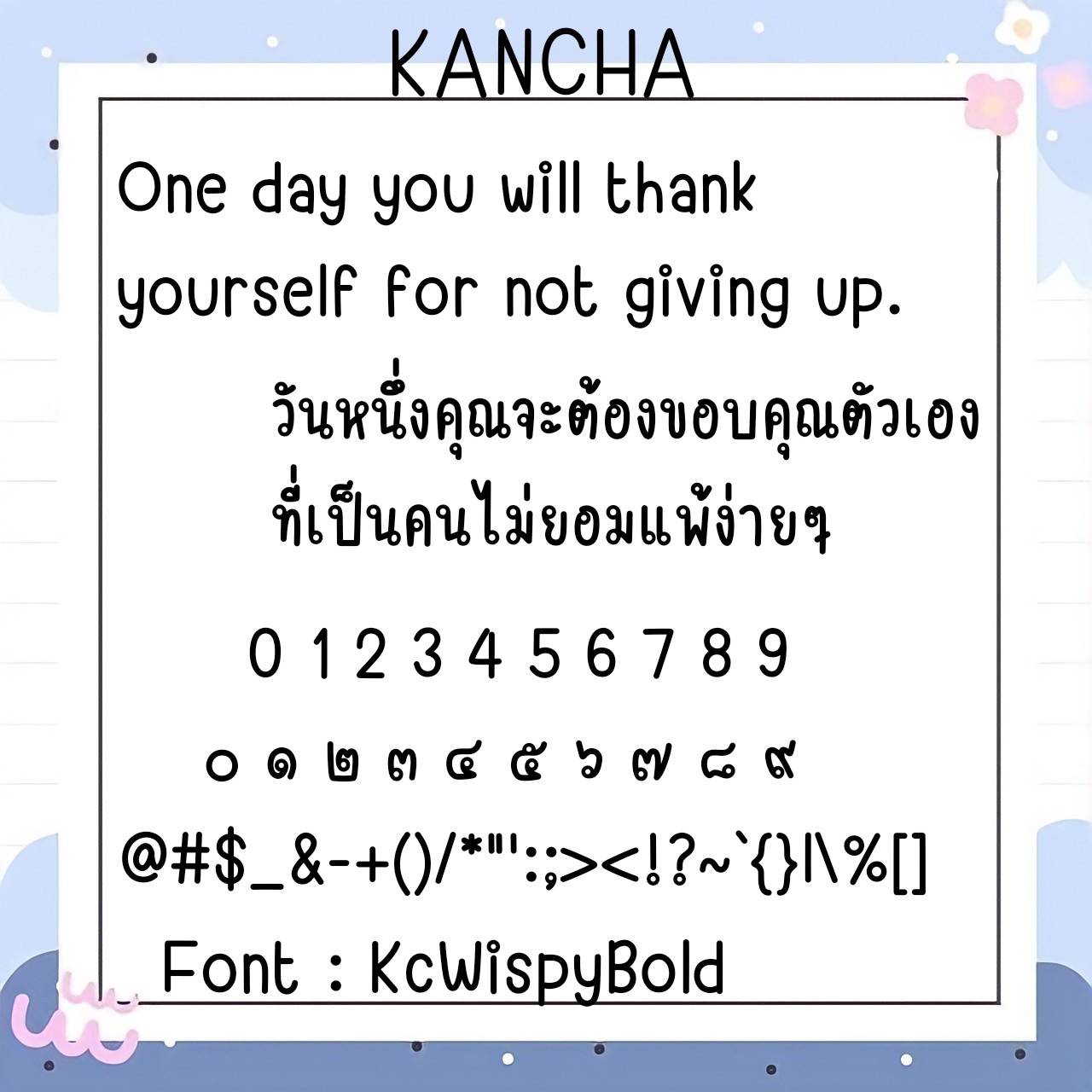
Font KcWispy
🔸ฟอนต์ตัวเล็กตัวน้อย น่ารัก แนววัยรุ่น
อ่านง่าย มีอิโมจิRabbitให้ในชุดด้วยค่ะ 🥰💙
🔹Small font, cute, teenager style.
Easy to read and rabbit emojis are included in the set.🥰💙